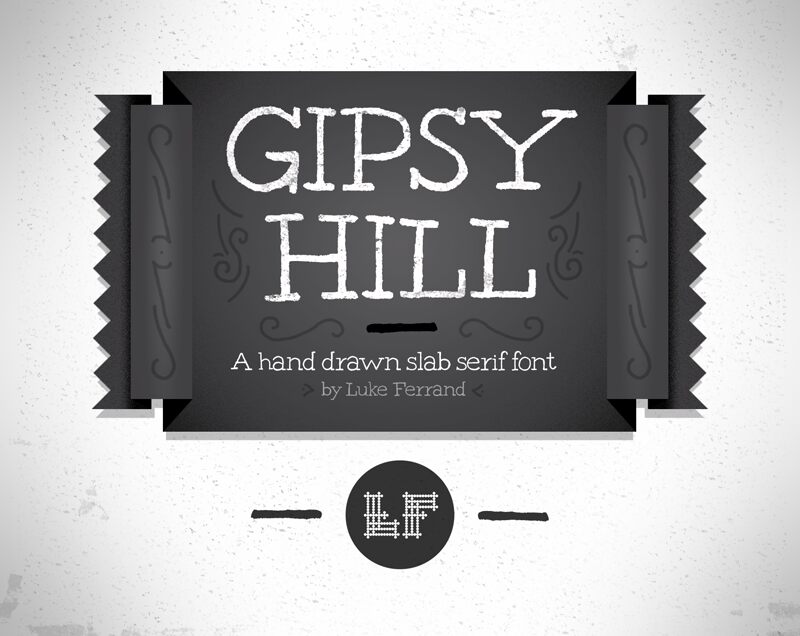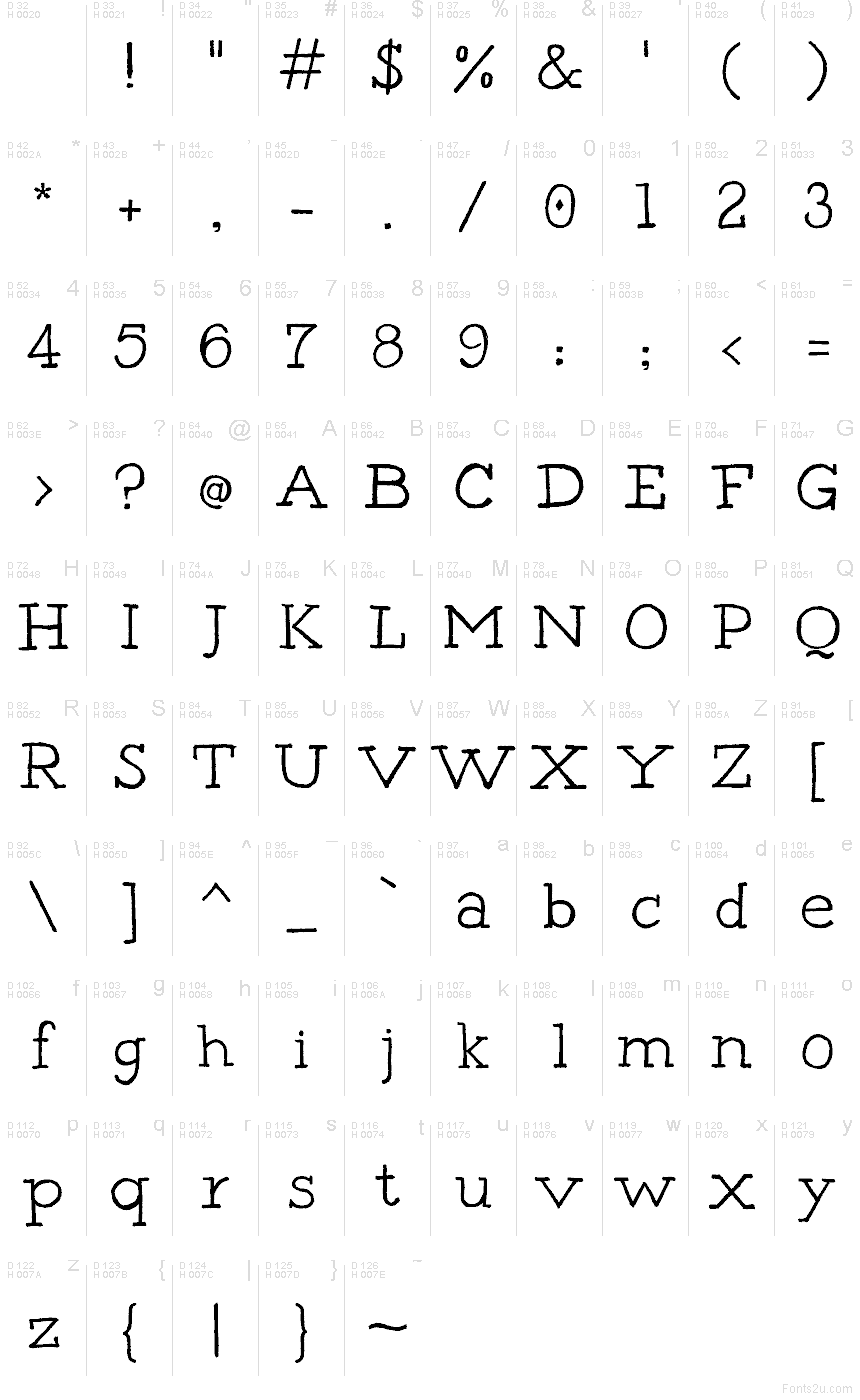
Gipsy Hill
Písmo Gipsy Hill od Lukea Ferranda je bezplatné ručne písané písmo s uvoľneným, skicovitým rytmom. Mierne drsné hrany dodávajú písmenám autentický, ručne kreslený pocit. Tvary zostávajú jednoduché a otvorené, s vysokými, úzkymi proporciami, zaobleným „g“ a dlhým, šikmým chvostíkom, vďaka čomu pôsobí celok neformálne, no nie chaoticky.
Gipsy Hill výborne funguje v brandingu, na plagátoch, obaloch, pozvánkach či grafike s citátmi, pretože jeho ležérne ťahy dodávajú osobný tón bez potreby ďalších dekorácií. Toto bezplatné písmo sa hodí aj na akcenty v logách, grafiku na sociálne siete, etikety a redakčné citácie, ak hľadáte písmo, ktoré pôsobí priamočiaro a jemne rustikálne.